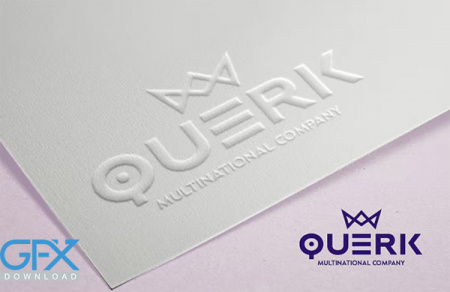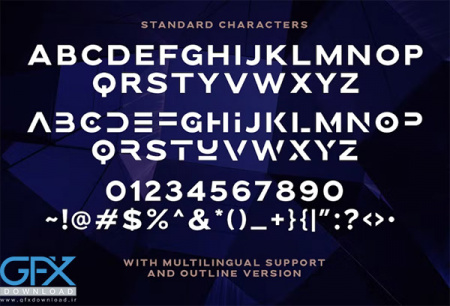
دانلود رایگان فونت لوگو Brolink Logo Font
دانلود رایگان فونت انگلیسی لوگو Brolink Logo Font
دانلود رایگان فونت انگلیسی طراحی لوگو Brolink Logo Font
Brolink یک فونت انگلیسی sans پررنگ با حروف کوچک منحصر به فرد است که طراحی شما را علمی تخیلی و مدرن جلوه می دهد. شما می توانید از این فونت برای هر هدفی استفاده کنید، به خصوص برای ساخت لوگو تایپ. می توانید حروف بزرگ و کوچک را با هم ترکیب کنید تا لوگوی خود را خواناتر کنید. برای دانلود رایگان فونت لوگو Brolink Logo Font از جی اف ایکس دانلود به ادامه مطلب مراجعه کنید.